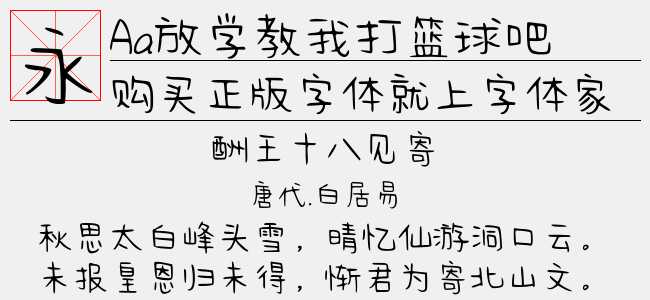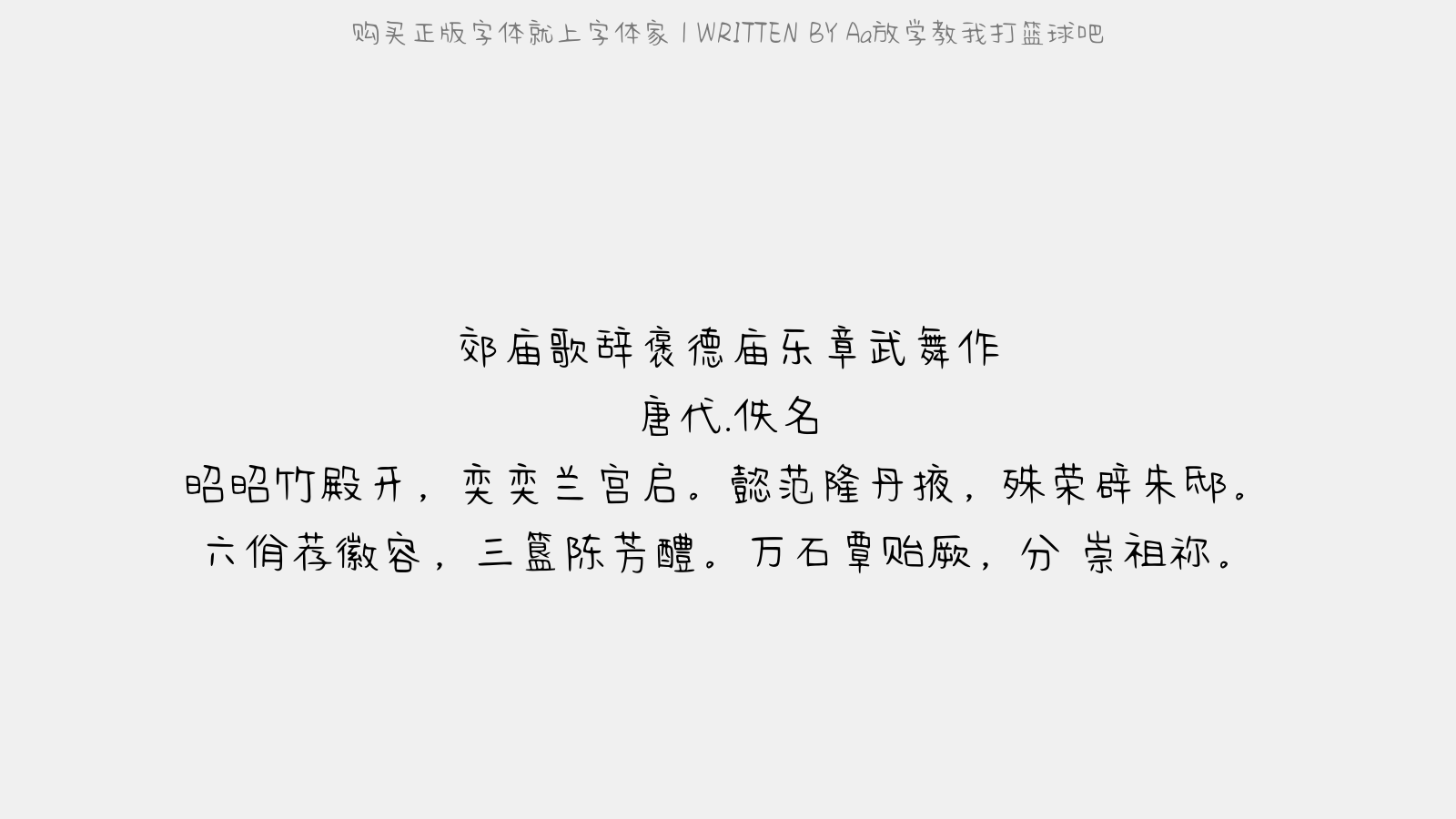
Aa放学教我打篮球吧
字体作者:Aa字库
字体名称:Aa放学教我打篮球吧
字体家族:Aa字库
书体类型:手写/印刷体
Aa放学教我打篮球吧
Aa放学教我打篮球吧是一款不错的艺术字体,由Aa字库出品,字体笔触纤细,书写流畅,拥有字符数8040和字形数8008,具有很好的视觉感,适合应用于艺术设计、平面宣传设计、网页设计,书法字帖等领域,需要的朋友可以前来本站下载。